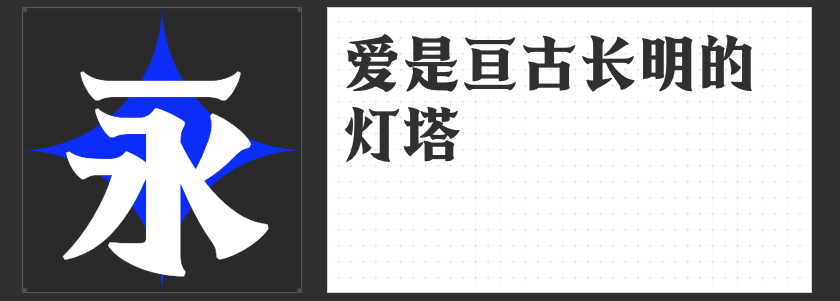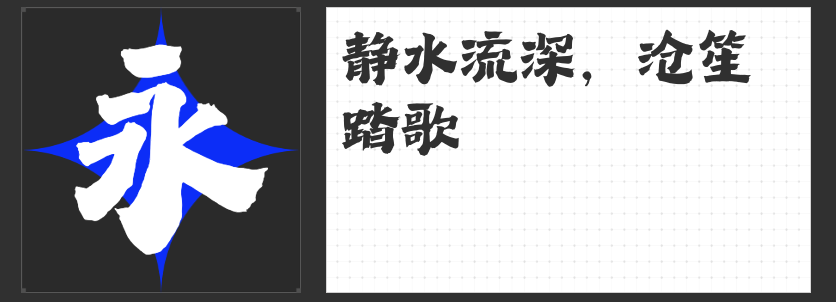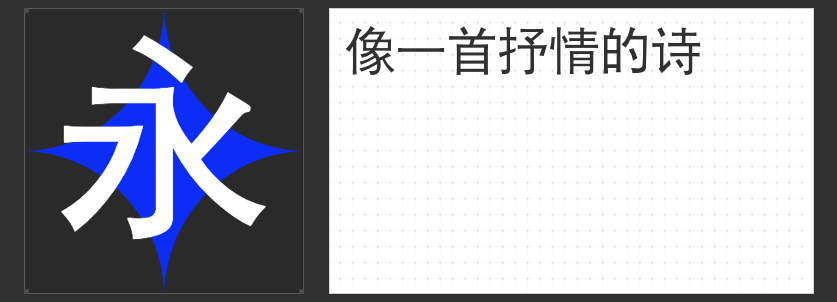
四款字体打造修仙游戏独特魅力
在设计一款引人入胜的修仙游戏时,字体的选择至关重要。合适的字体不仅能增强游戏的整体氛围,还能提升玩家的沉浸感。以下是四款精心挑选的字体推荐,旨在帮助您创造一个视觉上令人难忘的游戏世界。
1. 造字侠热辣隶简 —— 登录页面的灵魂
造字侠热辣隶简以其独特的风格,成为修仙游戏中登录界面和LOGO设计的理想选择。这款字体融合了隶书的古典美感与现代设计的简洁线条,给人一种既传统又时尚的感觉。它粗细适中的笔画和适度的留白空间,使得无论是在电脑屏幕上还是手机小屏上都能展现出色的表现力,为玩家的第一印象打下良好的基础。
2. 万人字造踏歌行体 —— 潇洒飘逸的风采
对于游戏内大标题、重要提示以及特殊场合的文本展示来说,万人字造踏歌行体是再合适不过了。这款毛笔字体带有明显的书法韵味,每一笔每一划都透露出一种飘逸潇洒的气息,仿佛能让文字随着玩家的指尖舞动起来。这种风格非常适合用来表现修仙世界中的仙气与灵动,让玩家仿佛置身于仙境之中。
3. 高手兵克侠客体 —— 复古神秘的风范
如果你希望在游戏中营造出一种神秘而复古的氛围,那么高手兵克侠客体会是你的首选。它的设计灵感来源于古代武侠小说中的侠客形象,每个字都充满了故事感。这款字体笔触有力而不失细腻,能够很好地表达出修仙者们行走江湖时那种既威严又不失温柔的性格特征,非常适合用于游戏内、宣传海报上的大标题设计。
4. 励字中等线简 —— 清晰易读的正文之选
在保证游戏内容传达准确性的前提下,励字中等线简为您的游戏内正文提供了最佳解决方案。这款字体以其简洁明快的线条和高度的可读性著称,即使在较小的字号下依然能够保持清晰度。它适用于各种类型的文本显示,无论是任务描述还是剧情对话,都能够给玩家带来舒适的阅读体验。
通过以上四款字体的巧妙运用,使修仙游戏将不仅在视觉上更加吸引人,还能从细节处体现出深厚的文化底蕴和精雕细琢的设计理念。记住,字体虽小,却蕴含着无限的魅力,选择正确的字体就是赋予游戏生命力的关键一步。